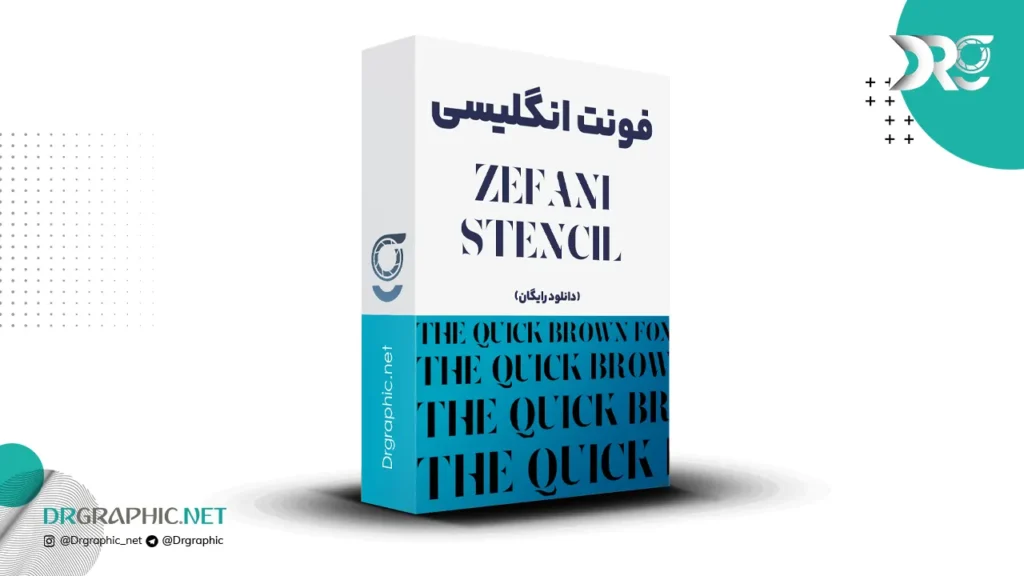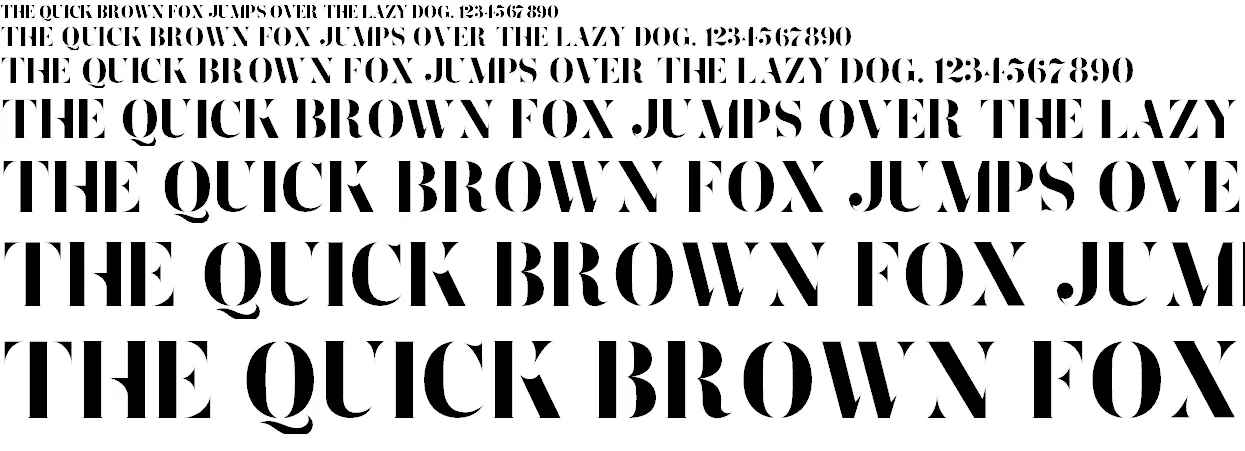
فونت انگلیسی Zefani Stencil
• مدرن و کاربردی
فونت جالب و مدرن انگلیسی Zefani Stencil یک فونت فوق العاده زیبا است که می‌توانید از آن در طرح و پروژه‌های گرافیکی مختلف استفاده کنید. شما میتوانید این فونت را به صورت رایگان از دکتر گرافیک دریافت کنید.
نمونه نوشته با این فونت: